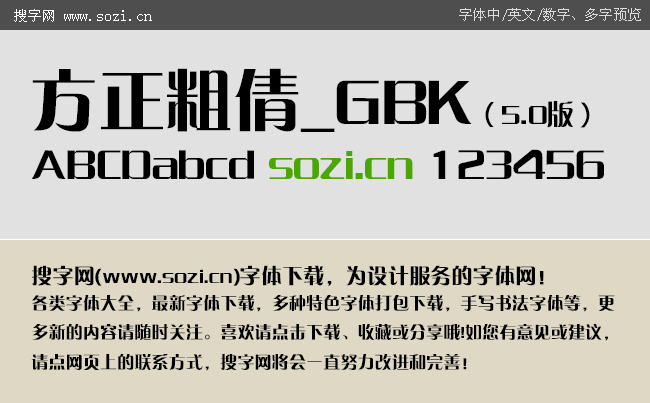
方正粗倩-GBK
搜字網(wǎng)給大家提供一款方正粗倩-GBK下載。GBK標(biāo)準(zhǔn)收錄漢字更全,粗倩體親切、幽雅、柔美和華麗,筆劃粗細(xì)對比強烈。精致、華貴、大氣、端莊,筆形富于變化,浪漫而又溫馨。,卻能給人以美的感受。適用于個人用品、化裝品、食品、家居廣告宣傳使用環(huán)境。